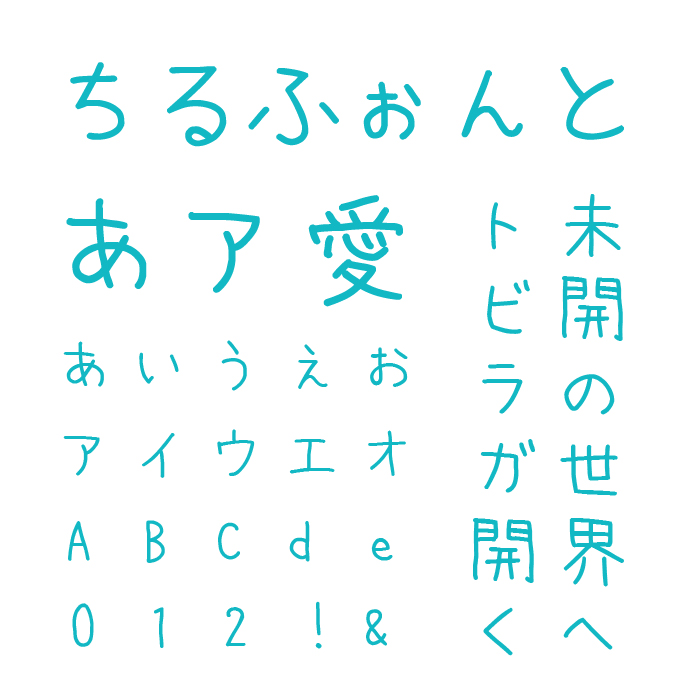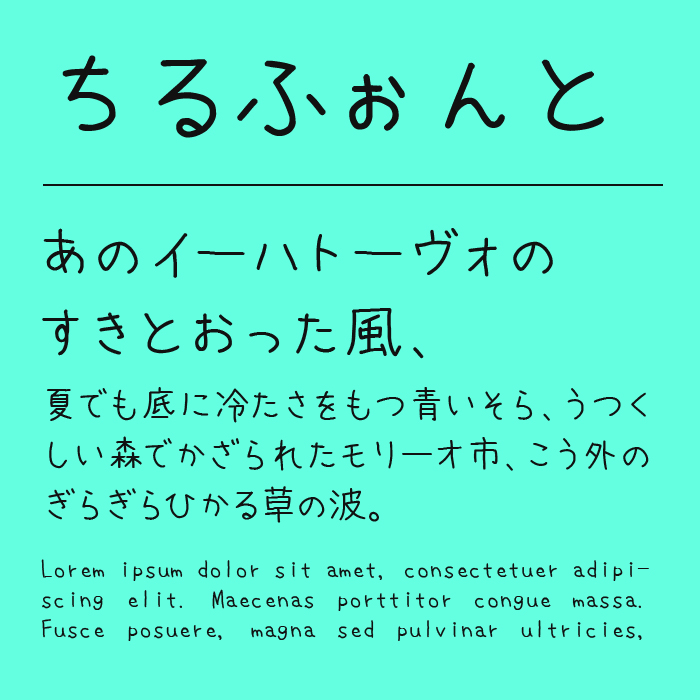
ちるふぉんとフォントは、細めの均一な線とゆったりとした字間が特徴の、ゆるくて軽やかでリラックスした手書きフォントです。
手書き風のやわらかさがあり、文章を読むと自然と肩の力が抜けていくようなチルな手書き文字がとても良いです。
そのため、カフェや雑貨、ライフスタイル関連の記事やZINEなどにぴったり合います。エッセイやコラムのテキストにも違和感なく馴染みます。英字との相性も良く、日英が混ざったデザインにもおすすめです。
収録文字は、漢字・ひらがな・カタカナ・アルファベット・数字・記号が収録。